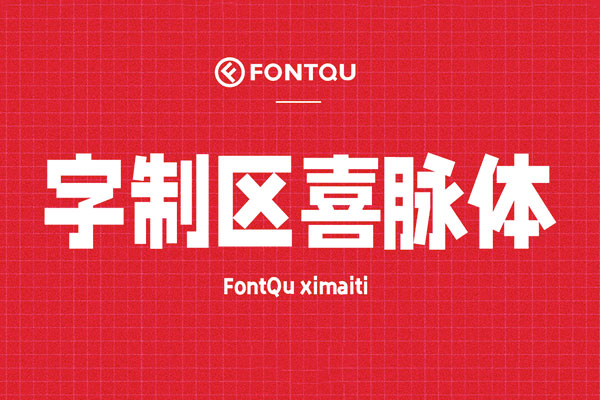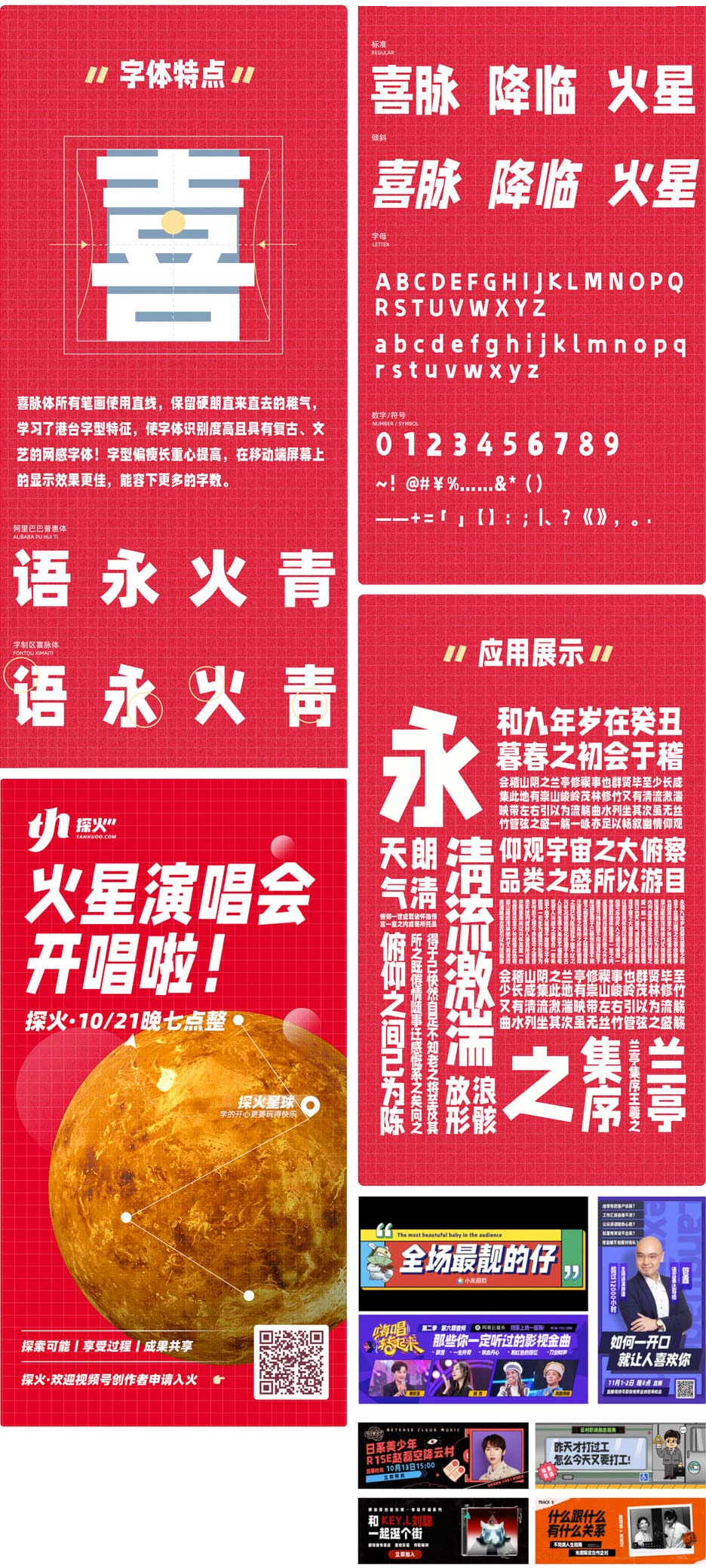
字制区喜脉体
字制区喜脉体是FONTQU团队推出的首款免费商业字体,于2021年1月1日发布,为新年送上祝福!
“随着5G技术和短视频行业的飞速发展,我国在这两个方面取得了领先地位。然而,字体文化的发展却相对滞后。许多创作者都缺少一款适合手机屏幕的免费字体,以及一款具有网络感的免费综艺字体。为了弥补这一缺陷,为即将到来的30岁献上一些热血和喜爱,我们推出了这款名为字制区喜脉体的字体!”
字制区喜脉体采用直线设计,保留了简洁明了的笔画特征,同时借鉴了港台字体的特点,使字体具有高识别度、复古和文艺气息。字型偏瘦长,重心提高,在移动设备屏幕上显示效果更佳,能够容纳更多文字。
字制区喜脉体效果预览
字制区喜脉体字体效果预览